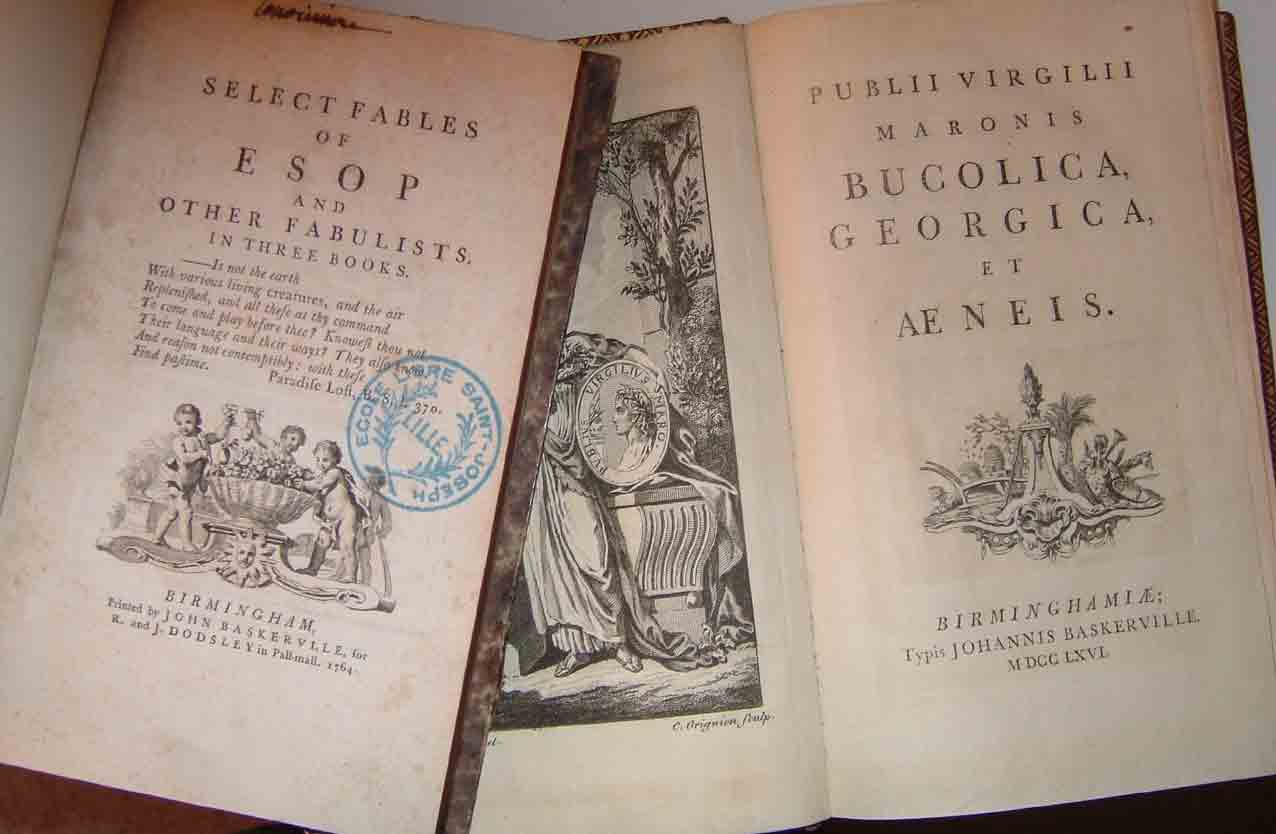
Vous m'obligez à raconter ma vie, ce que je ne voulais pas faire... Le Baskerville est un caractère que j'affectionne depuis bien longtemps pour son élégance et sa grande lisibilité. J'essaie de l'utiliser toutes les fois que je peux le faire intelligemment et ce pour les raisons précitées. Et je n'ai pas attendu l'ordinateur et la déclinaison Berthold pour le faire. Je l'ai également utilisé en photocomposition (ne me demandez pas lequel c'était : je sous-traitais), j'en ai également en plomb dans mes casses, et j'ai également du Baskerville de Baskerville dans ma bibliothèque. Dois-je vous avouer que c'est celui-là que je préfère parce qu'il n'est pas trafiqué. Hélas, je ne puis que le regarder... Bien à vous, Christian Laucou. ----- Original Message ----- From: "Thierry Bouche" <thierry.bouche@xxxxxxxxxxxxxxx> To: <typographie@xxxxxxxxxxxxxx> Sent: Wednesday, May 19, 2004 12:31 PM Subject: Re: [typo] Typo des livres de poche > Le mardi 18 mai 2004 à 19:04:56, Christian Laucou-Soulignac écrivit : > > CLS> Non... je maquette une collection de semi-poche en Baskerville de chez > CLS> Berthold, justement pour ne pas utiliser du... heu... c'est quoi déjà son > CLS> nom ?... > > On aurait préféré que ce soit pour une meilleure raison ! Il est pas > mal, le Baskerville de chez Berthold (enfin, ça dépend duquel on > cause...) > > > Thierry Bouche > >